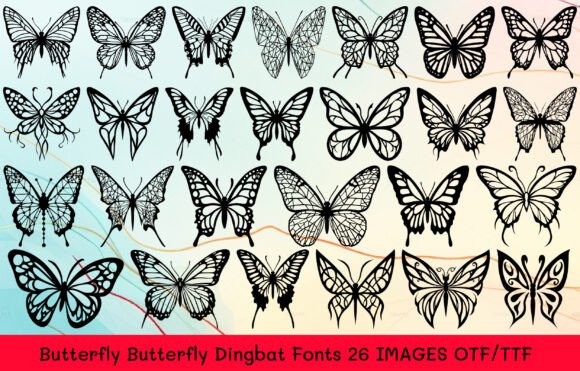
Butterfly Butterfly
قد يكون العثور على عناصر التصميم المناسبة أمرًا صعبًا، ولكن Butterfly يقدم مجموعة استثنائية ترتقي بعملك على الفور.
سواء كنت تقوم بإنشاء منتجات الطباعة عند الطلب أو دعوات الزفاف أو رسومات وسائل التواصل الاجتماعي، فإن Butterfly هو الخيار المثالي.